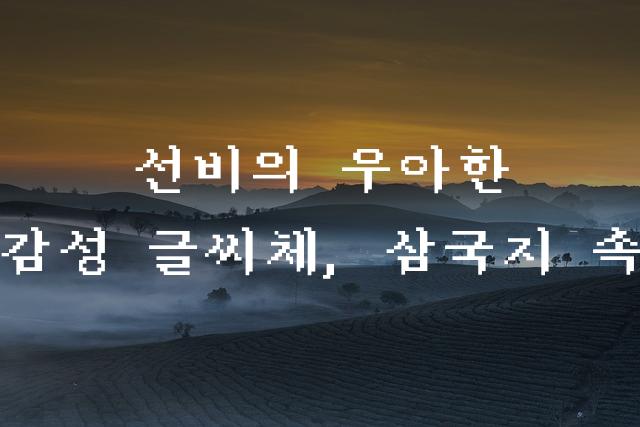
도스고딕은 레트로 감성이 가득한 픽셀 도트 스타일의 폰트로, 디지털과 아날로그의 경계에서 독특한 매력을 발산합니다. 각 글자의 구성이 마치 과거 게임 콘솔을 연상시키며, 모던하면서도 빈티지한 느낌을 제공합니다.
도스고딕은(는)
픽셀/코딩, 레트로, 감성적인, 복고풍, 게임 느낌 계열의 생김새를 가지고 있으며
웹/앱 디자인, 보고서/문서, 출판물 제목 등에서 자주 활용되며, 효과적인 메시지 전달에 적합합니다.
이 폰트는 출판/미디어, 기술/IT, 금융/비즈니스 분야에 잘 어울리며,
명확한, 전문적인, 단순한 느낌을 담고 있는 것이 특징입니다.